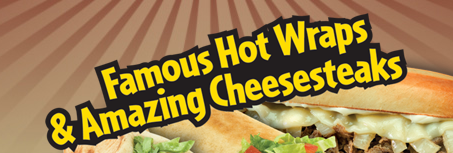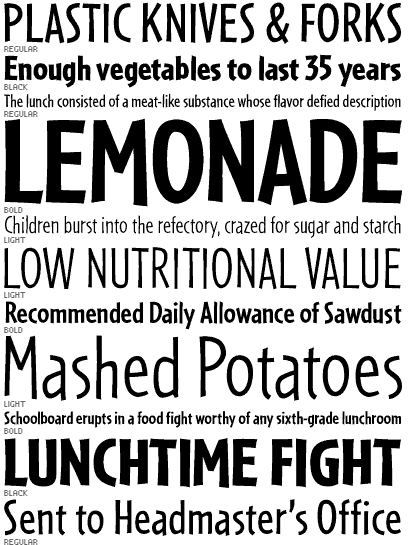
Suche diese oder so ähnliche Schriften, bevorzugt free fonts, aber auch kostenpflichtige.
Das müsste die Cafeteria Bold sein. Diese liegt auch illegal im Netz rum, wie ich gerade ergoogelt habe. Finger weg! Hier eine unbedenkliche Quellen mit echt freien Ersatzschriften: http://www.identifont.com/free-fonts?5 Ansonsten könntest Du in der Kategorie Comic auf D*f*nt suchen.
Prater Sans benutzt auch der Spiegel, daher wäre die Schrift für mich ein No-Go. Besitzer von Bitstream-Sammlungen (zB Corel Draw) können sich die „Mr Earl BT“ mal ansehen. Dann gibt es noch die „Big Bimbo NC“ und deren Weiterentwicklung/Ableitung „Hauracherell“ sowie die „Curse Casual Jve“. Dann habe ich hier noch „Sala de Fiestas“ in den Daten. Wenn es nur Großbuchstaben sein sollen wäre die freie Schrift „Single Sleeves“ von Fic Fieger interessant. Alternativ dazu die „Cartoonsix“. Die Links und die Lizenzen muss man sich aber selber ergoogeln, dazu bin ich jetzt zu faul. Ich habe hier nur Mr Earl BT und Single Sleeves, welche ich definitiv nutzen darf.
Wenn Du mit einem Mac arbeiten solltest, wäre auch noch die Skia interessant, weil im Betriebssystem integriert und auch für kommerzielle Zwecke bedenkenlos einsetzbar.
Prater Sans benutzt auch der Spiegel, daher wäre die Schrift für mich ein No-Go.
Das Erscheinungsbild des Spiegel wird typografisch zuallererst durch seine Wortmarke sowie den eigens entwickelten und gleichnamigen Font von Luc(as) de Groot geprägt. Beides hat mit der Prater Sans nichts gemein. Daher wäre es für mich kein Grund, wenn für Specials oder ähnliches auch mal die Prater Sans eingesetzt werden sollte, diese für andere Zwecke nicht mehr zu verwenden. Bei Deiner Philosophie müsste man im Gestaltungsalltag die halbe Schriftsammlung ignorieren. ;-)